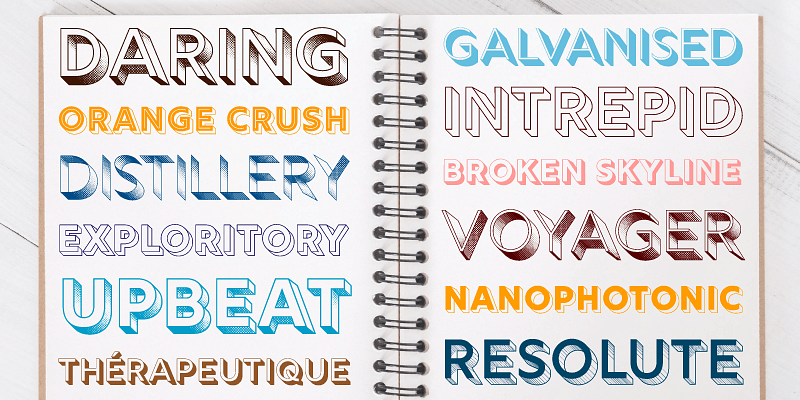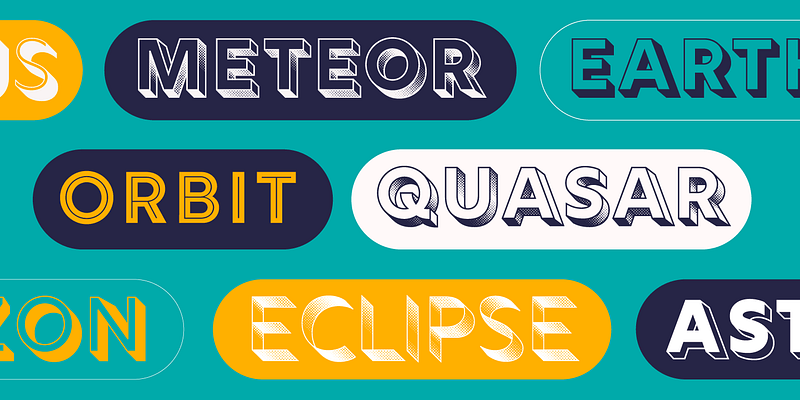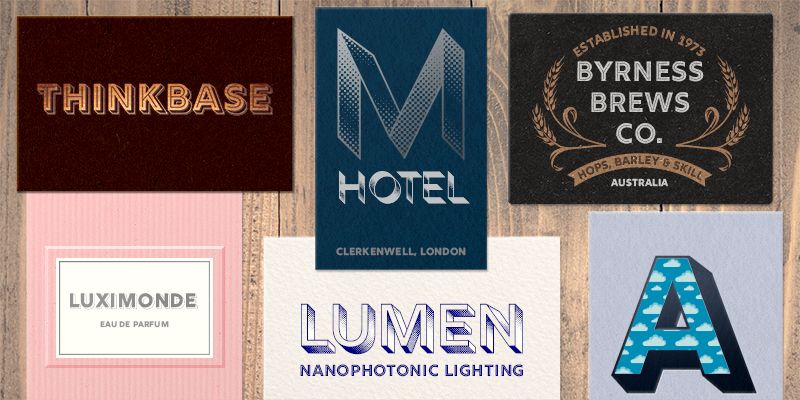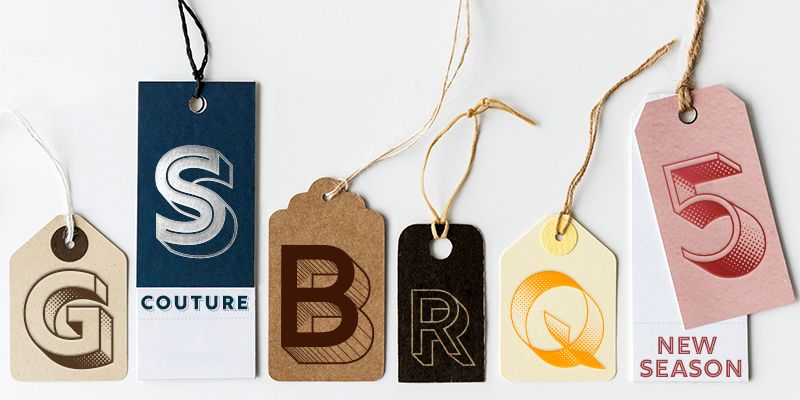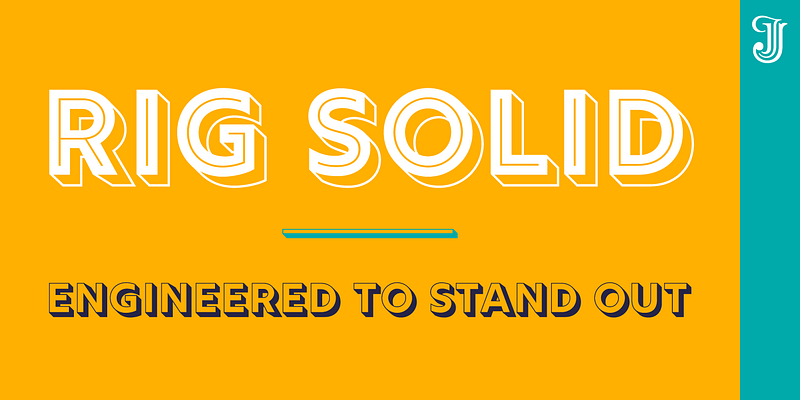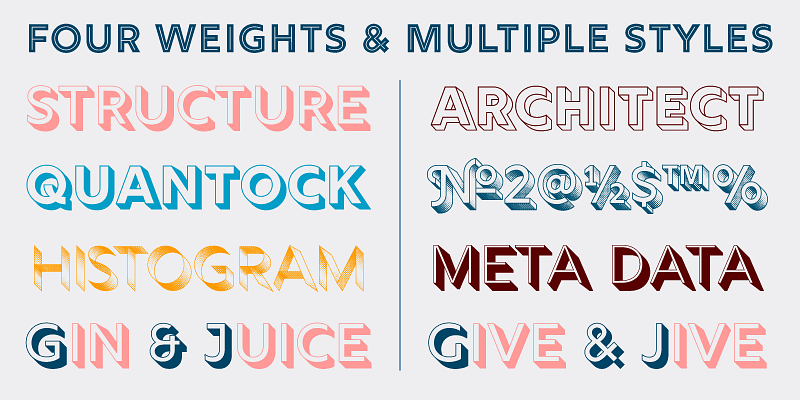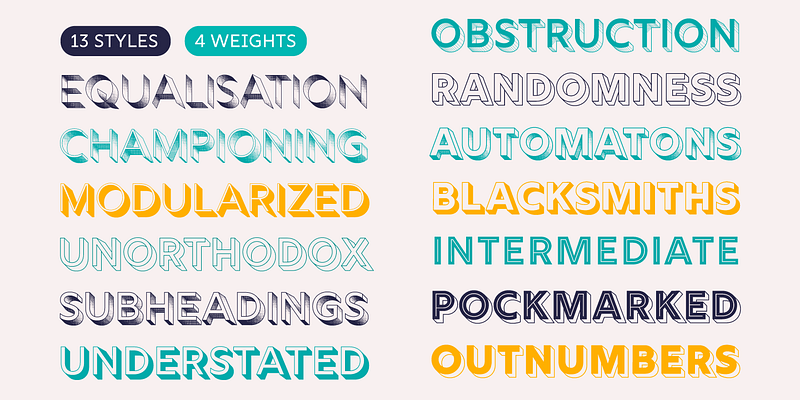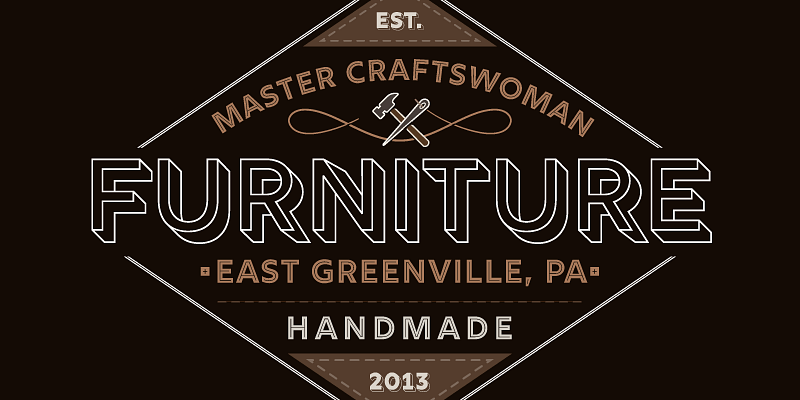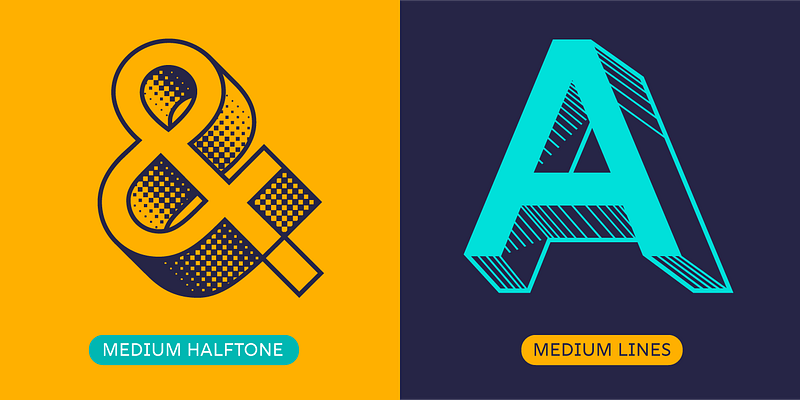
Uma ampla variedade de fontes 3D inovadoras em quatro pesos. Os estilos de meio tom marcantes da Rig Solid adicionam textura aos títulos, enquanto os estilos robustos e preenchidos adicionam um impacto visual a qualquer tipografia.